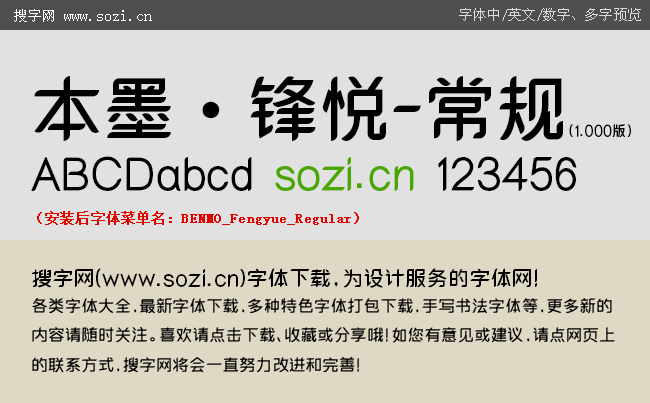
本墨·鋒悅(常規(guī))
搜字網(wǎng)提供一款非常藝術(shù)的本墨·鋒悅(常規(guī))下載,本墨·鋒悅是一款字形方正的中文藝術(shù)字體,該字體極具藝術(shù)感,簡(jiǎn)潔大方,適用于包裝印刷、廣告設(shè)計(jì)、平面設(shè)計(jì)、書(shū)籍報(bào)紙等領(lǐng)域。